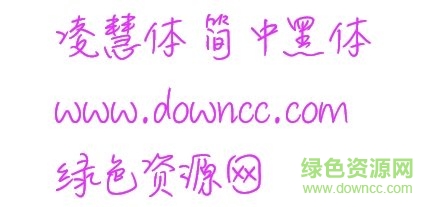
蒙纳凌慧体 简 中黑体
凌慧体是蒙纳字体中的一款简中黑体,有草书飘逸质感,实则是一款硬笔书法字体,笔画流畅文字清晰,艺术效果出色,如果你在找这款字体,就来绿色资源网下载吧!
蒙纳凌慧体 简 中黑体介绍
蒙纳凌慧体,也写作蒙纳凌惠字体、MLingWaiPHK,在ios10系统中比较常见,是一款标准的简体中文字体,无需刷入繁体即可正常表达。
凌慧简体是一款免费钢笔手写体,结构宽绰、秀美,整体笔画书写流畅、随性,你可以将其用于海报设计、杂志设计等方面!